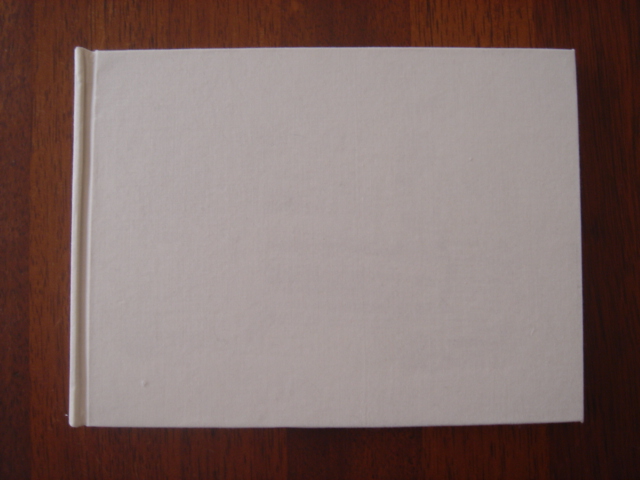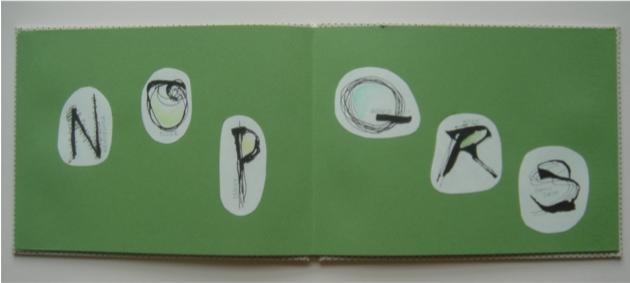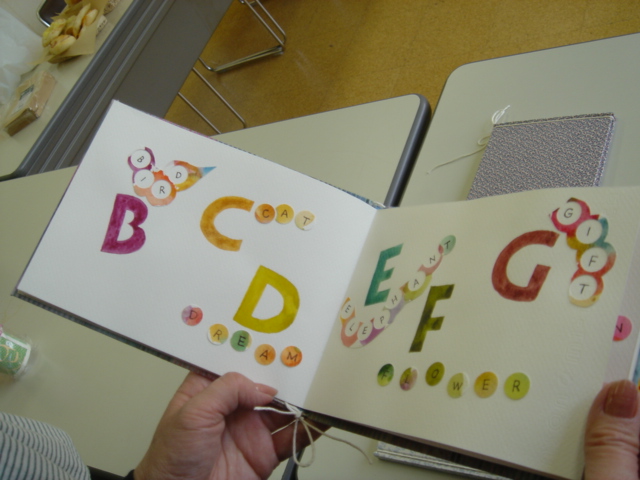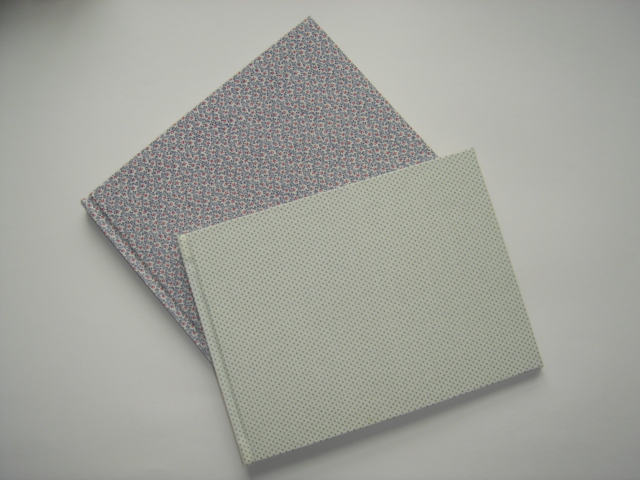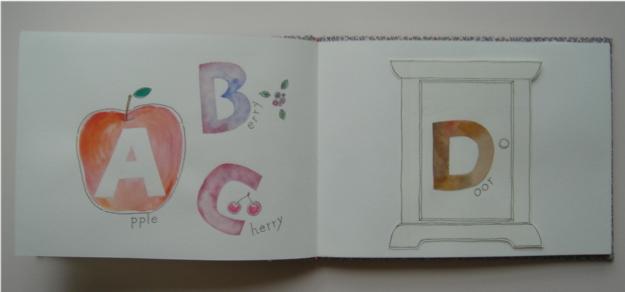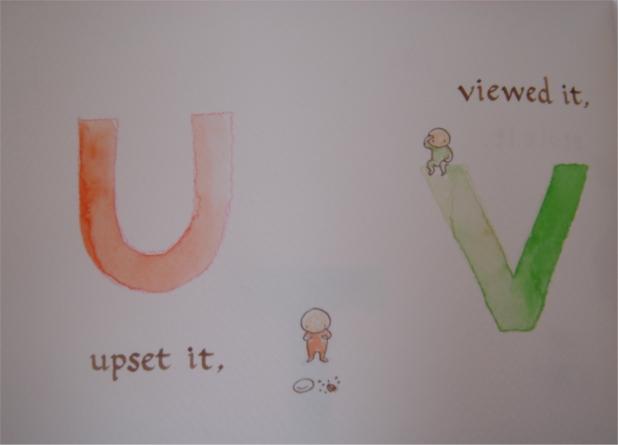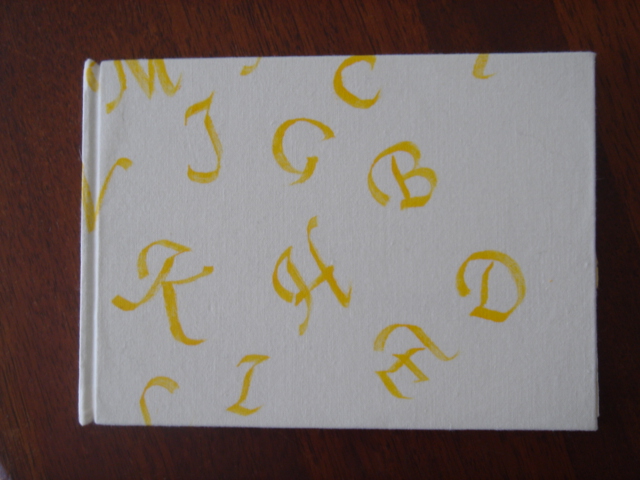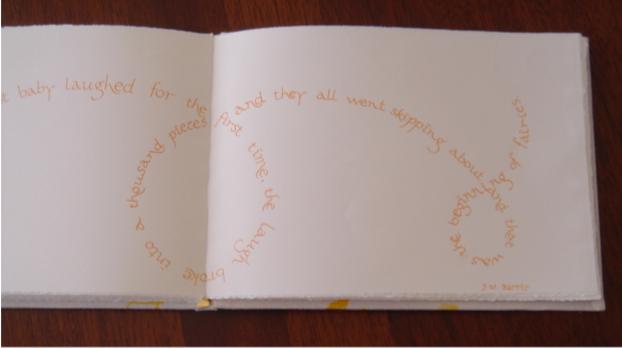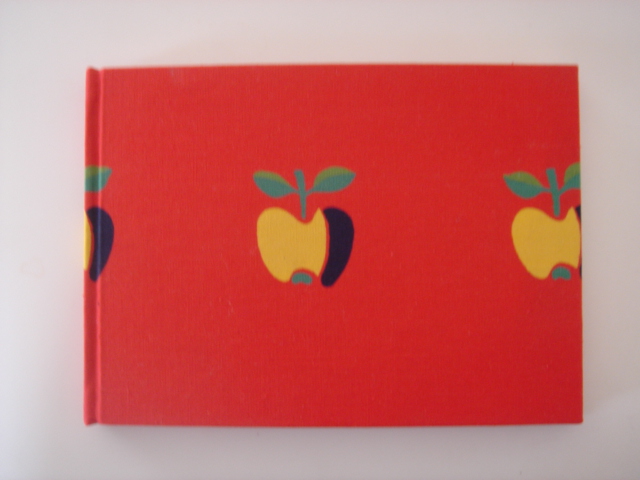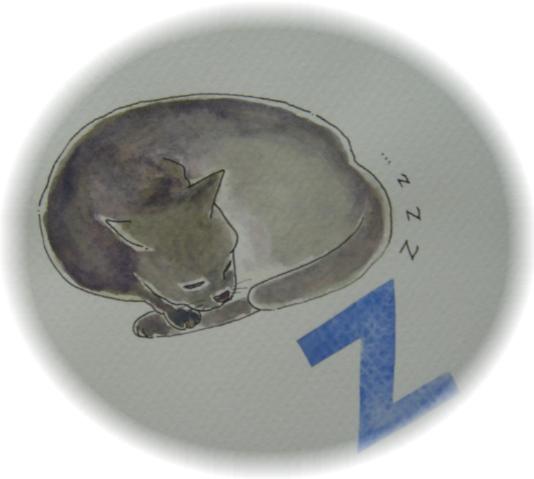
ABCブックのその後
春に製本ワークショップを開きまして、Kyokoさんに絵本製本を教えてもらいました。
こんなにいろいろな布地を貼った表紙のブックたち。このあと家に持ち帰り、しっかり重石をしました。
さて、その中身もさまざまでした。カリグラフィーを始めたばかりの人も頑張りました!!
Kyokoさんがワークショップのサンプルとして持ってきてくださったのはこんなふうにカラフルカワイイABCでしたが
今回見せてくださったのは細かい水玉の表紙、中身はこんなに渋い&表情豊かなアルファベットがルーリングペンで書かれて並んでいました。さすが〜
小花模様のブックはTさんのもの。このDoorは実際に開くんですよ!
どのページにもストーリーがあり、更に仕掛けもあって、驚き楽しめる絵本になっていました。
シンプルなベージュの布地はMさんのです。中は「My ABC Phonics Book」とタイトルがついていて
このまま英語教材としても使えそうです。色鉛筆のやさしい色とタッチで心温まる作品です。
こんなぴったりの布地を見つけるなんて、布持ちのSさんならでは、ですね。
アップルパイのお話をモチーフに、かわいいヒトが大活躍しています。
表情がなんともいえず…文字の色のにじませ方もきれい。
表紙の布も手書きなのはYさん。
急遽ワークショップに参加することになり、短い時間で中身を仕上げたのでした。(お疲れ様でした)
今回の製本ではページはすべて背中合わせに貼り合せてあるので、自由に左右のページを行き来して書くことができます。
初めて作ったブックは宝物
Tさんの描いたネコちゃん、人気者。